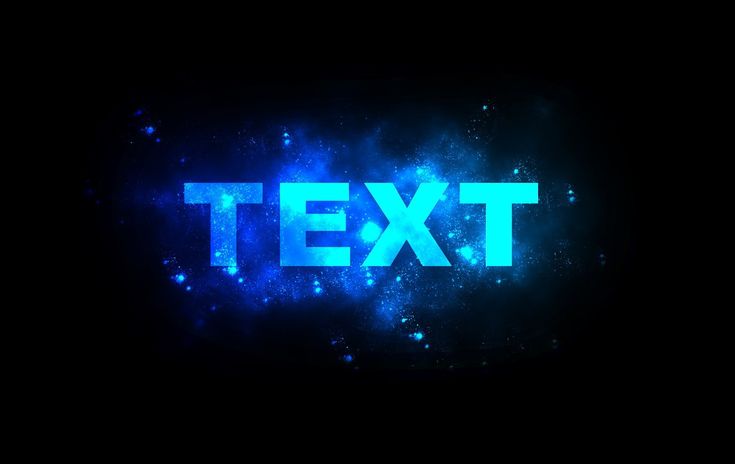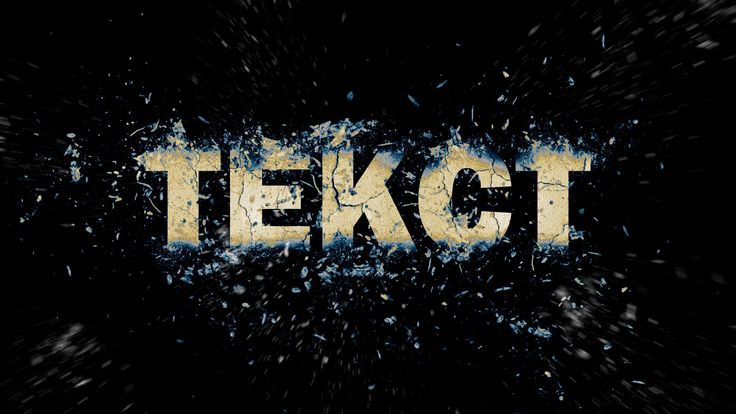
Как написать в фотошопе красивый текст: 5 лучших способов
Доброго времени суток уважаемые читатели!На связи Федор Лыков. Сегодня я вам подробно расскажу, как написать в фотошопе красивый текст. Желаете повысить уровень владения фотошопом? Или вы оформляете страницы в социальных сетях? Если хотя бы на один из вопросов ответили «да», то тогда вы зашли по адресу.
Запаситесь терпением, ручкой, блокнотом и дочитайте статью до конца. Уверен, что у вас все получится и результат приятно удивит.
Чтобы начать бегать, сначала нужно научиться ходить.
В любом деле нужно начинать с простого, постепенно переходя к сложным действиям. Согласитесь, ведь мы в начале учим буквы и только потом читать, а не наоборот. Также и здесь. Сначала мы освоим простые функции программы, а затем будем писать простой, стандартный текст, а далее красивые и уникальные надписи.
И так приступаем к конкретным действиям.
- Открываем программу Photoshop и загружаем картинку, на которой будем делать текст.
- В панели инструментов с левой стороны найдите заглавную букву Т, нажмите на нее. Если нажмете правой кнопкой, то можете выбрать стиль написания текста: горизонтальный, вертикальный или текст-маска.
- Появившемся курсором нажмите на картинке. При этом определитесь с местом, на котором будете делать надпись.
- В верхней панели инструментов можно выбрать шрифт, размер, выравнивание. И текст готов.
Также можно менять цвет надписи. Нажмите на квадратик и выберите нужный цвет. Если вас не устраивает цветовой выбор, то оттенок можете подобрать самостоятельно в правом окне. Просто переместите кружок в нужное место. А если вы знаете код цвета, то просто укажите его.
Функция деформацииХотите, чтобы ваш текст как-то по-особому заиграл, необычно располагался? Тогда вам поможет функция деформации. Она располагается в верхней панели инструментов и обозначен буквой Т подчеркнутой дуговой линией.
Воспользоваться ею очень просто. Выделите надпись и нажмите правой кнопкой мыши на этот знак. Откроется список всех эффектов: дуга, арка, флаг, рыбий глаз и все возможные варианты. Делайте выбор по собственному усмотрению.
3D эффектНравятся ли вам надписи с эффектом 3D? Они такие объемные и кажется, что надпись оставляет за собой след. А ведь это сделать очень просто.
- Перейдите в слой теста, но не выделяйте его.
- Нажмите на 3D режим. Он находится в верхнем меню.
- Объемный текст делается при помощи меню «Новая сетка из градаций серого».
- Преобразовать слой можно при помощи параметра «Новая структура из слоя».
Также той функцией можно менять как цвет самого текста, так и назначать цвет его тени, а еще делать красивую обводку, свет, особое его расположение на фоне. В общем, возможностей много, главное фантазия. Попробуйте все возможности 3D эффекта.
Надпись с эффектом золотаДля примера давайте сделаем практическую часть и создадим красивую золотую надпись. Для этого будем выполнять следующие действия:
Как создать в фотошопе красивый текст?
- Выбираем инструмент Т. Включаем CapsLk и шрифтом Big Bottom Cartoon пишем текст, при этом устанавливаем параметры 300 пт и Трекинг на 75.
- Нажимаем комбинацию Ctrl+J для дублирования текстового слоя.
- Возвращаемся к оригинальному слою. Заходим в Слои, далее в Стиль слоя и потом Тень. Выставляем параметры: непрозрачность – 32%, смещение – 11, размер – 9.
- Делаем еще одну копию и на нее выставляем следующие параметры: непрозрачность – 50%, смещение – 36, размер – 50.
- Переходим в оригинальный текстовый слой и делаем копию. Нажимаем правой кнопкой на копию текста и делаем выбор на Вставить стиль. На оригинальном слое делаем заливку на 0.
Эти неоновые вывески очень забавны и просты в настройке. Они на 100% многоуровневые, а также на 100% векторные. Простое редактирование с вашим собственным текстом или, если вы хотите создать свой собственный шаблон, я включил файлы ASL.